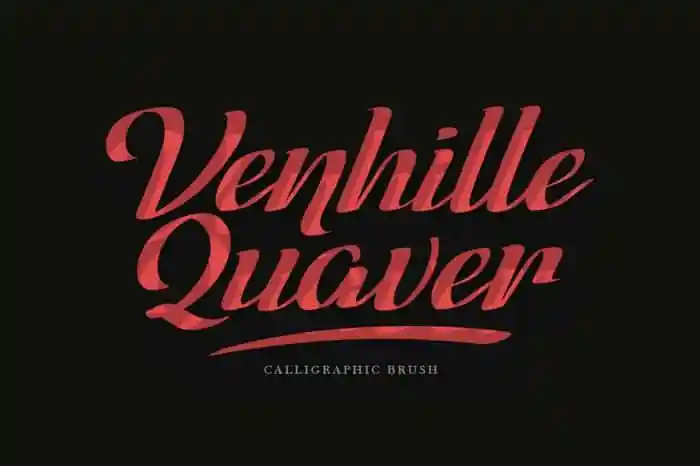
Venhille Quaver Script Font – Download Grátis
A fonte “Venhille Quaver Script Font” é uma peça excepcional do mundo dos recursos visuais digitais, especialmente para aqueles que buscam algo autêntico e limpo na tipografia. Com seu estilo de escrever com originalidade, a “Quaver Script Font” oferece um toque único em cada curva, dando à sua composição um aspecto naturalmente encantador. Esta fonte é perfeita para criar materiais que expressam uma personalidade única e autêntica – seja em design editorial, marca ou mesmo em artesanato digital. Convidamos você a explorar o mundo de “Venhille Quaver Script Font”, onde cada letra é uma oportunidade para experimentar a fidelidade da arte da escrita, revestida com um toque pessoal e criativo.